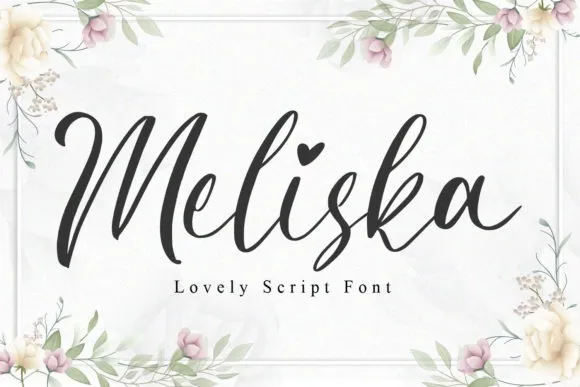
A fonte ‘Meliska Font’ é uma elegante fónta script com aparência natural de escrita à mão. É perfeita para uso em logotipos, cartões de agradecimento, citações e posteres, ideal para identidade visual, cartão de visita, papel de parede, títulos de design, cabeçalhos de blogue, frases artísticas ou estilismo tipográfico moderno. Perfeita para projetos DIY e qualquer propósito que deseje dar um toque atraente e atual em seu trabalho de arte ou design. Designado e compartilhado pela NissaStudio, é uma escolha excelente para capturar o estilo de desenho à mão ou temas de pintura aquatônica nas suas criações.